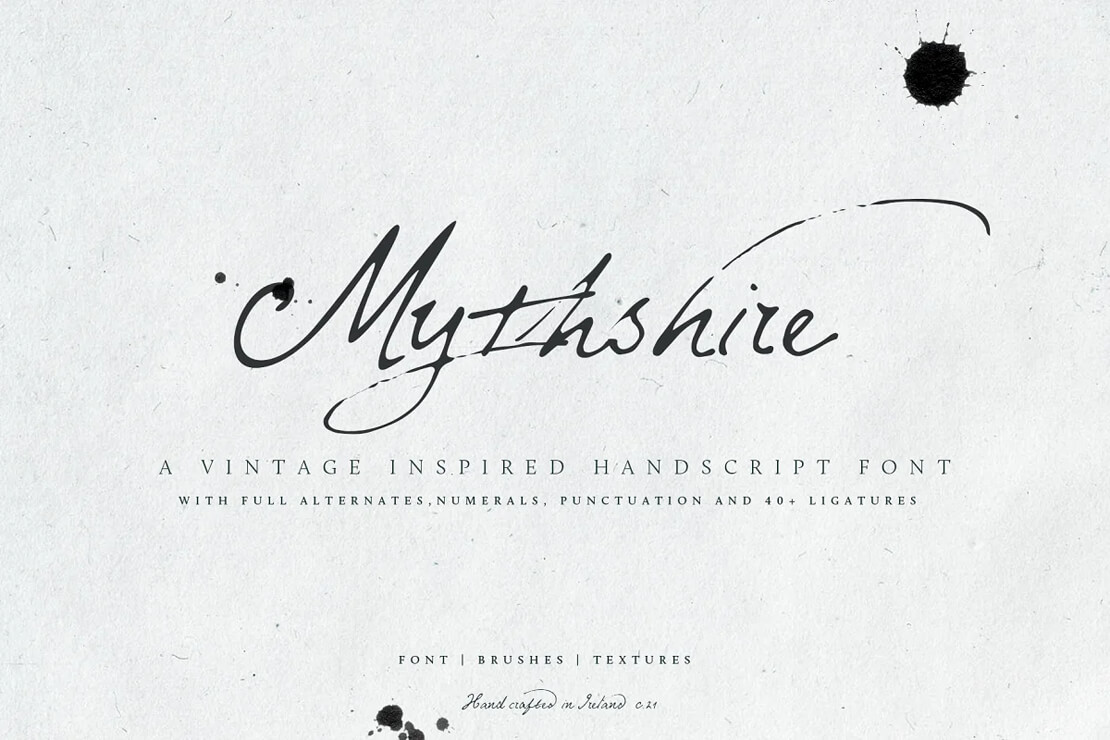
Mittelalterliche Schrift kreativ interpretiert: Medieval Fonts
Mittelalterliche Schrift hat eine faszinierende Anziehungskraft, die durch detailreiche und stilvolle Fonts Ausdruck findet. Die Epoche inspiriert zahlreiche Kreative, die moderne Displayfonts im prunkvollen und mystischen Look gestalten. Diese Übersicht zeigt ausgewählte mittelalterliche Schriftarten im zeitgemäßen Stil.
Mittelalterliche Schrift
Faszination Mittelalterliche Schrift
Mittelalterliche RitterrüstungSchriftarten, die das Mittelalter reflektieren, haben in Bereichen wie Fantasy-Literatur, Rollenspielen, Historiendramen und Videospielen eine große Bedeutung. Mittelalterliche Schrift verleiht diesen Projekten Authentizität und Tiefe. Dabei sind viele dieser Fonts Neuschöpfungen, inspiriert durch gotische und frakturartige Formen, die das ästhetische Bild des Mittelalters prägen.
Zu den historischen Einflüssen zählt die Fraktur-Schrift, die in der Gotik verwurzelt ist und heute oft mit dem Mittelalter in Verbindung gebracht wird. Die hier vorgestellten Fonts nehmen diese Stilrichtungen auf und verbinden sie mit modernen typografischen Features wie alternativen Zeichen und Swashes, die mehr gestalterische Freiheit ermöglichen.
Mittelalterliche Schriftarten zum Downloaden
Diese Auswahl zeigt Beispiele für mittelalterliche Schriftarten, die kostenfrei oder kostenpflichtig erhältlich sind und eine historische, aber dennoch moderne Atmosphäre erzeugen. Typische Einsatzgebiete sind Branding, Covergestaltung für Romane, Eventposter oder Kleidung. Mit variierenden Opentype-Features wie Ligaturen und Swashes werden die Fonts für kreative Projekte nutzbar.
Mittelalterliche Schrift von Creative Media Lab
Mittelalter-Schrift Baselard von KadekUnter dem Label „Creative Media Lab“ bietet Designer Kadek Schriftarten im mittelalterlichen Stil an, darunter Baselard*, Lordish* und Cattedrale*. Diese Fonts sind stark kalligrafisch geprägt und eignen sich für den Einsatz auf Labels, in der Mode oder im Bereich Gothic.
Belmont – Ein Fantasy-Font mit mittelalterlichem Flair
Belmont Fantasy- und Mittelalter-FontDer Font „Belmont“ bringt mittelalterliche Schriften mit einem Fantasy-Twist und bietet Schnitte für verschiedene Anwendungen. Internationaler Sprachsupport und alternative Zeichen machen Belmont für zahlreiche Projekte interessant.
Wolvercote – Inspiration durch Fantasy-Romane
Wolvercote - von Fantasy-Romanen inspirierte SchriftartMit „Wolvercote“ hat Christian Laliberte eine von Fantasy-Romanen beeinflusste mittelalterliche Schrift geschaffen. Die geschwungenen Formen und der Vintage-Stil machen diesen Font besonders für Projekte im Literatur- oder Film-Bereich interessant.
Mythshire: Mittelalterliche Handschrift
Mythshire: Vintage inspired Handscript FontDie Handschrift „Mythshire“ erinnert an historische Kalligrafie und verleiht Texten einen authentischen, eleganten Touch. Enthalten sind zahlreiche Ligaturen und alternative Zeichen, die die mittelalterliche Schrift abrunden.
Candelabra und andere Gothic-Fonts
Der Medieval Font CandelabraDer Font „Candelabra“ von Twinbrush Image Forge ist ideal für Fantasy-Genre-Anwendungen und wirkt mystisch und dunkel. Perfekt für Buchcover, Kleidung und mehr.
Aviorte: Ritterliche Mittelalterliche Schrift
Aviorte Mittelalter Font„Aviorte“ bringt einen Hauch von Ritterromantik und ist für zahlreiche Einsatzgebiete geeignet – von Branding-Projekten bis hin zu T-Shirts und Abzeichen.
DreiFraktur – eine kostenlose mittelalterliche Schrift
Kostenlose Mittelalter-Schrift DreiFraktur„DreiFraktur“ von Jay Cobs orientiert sich an gotischen Stilen und ist kostenlos verfügbar, ideal für private Projekte oder Retro-Designs.
Solaire und Exocet – Historisch inspirierte Schriften
Solaire: H. P. Lovecroft Font„Solaire“ und „Exocet“ verkörpern den mystischen Charakter des Mittelalters und passen gut zu düsteren und phantastischen Szenarien. Während „Exocet“ von Blizzard für „Diablo“ verwendet wurde, ist „Solaire“ durch literarische Inspirationen geprägt.
Asgaard und Magensburg
Vikinger-Schriftart für Mythologie„Asgaard“ bietet sich für nordische Mythologie-Projekte an und lässt sich durch seine Layer gut individualisieren. „Magensburg“ ist eine kostenlose Schrift, die besonders in Logos oder für private Projekte eine mittelalterliche Atmosphäre erzeugt.
Endor und Braveheart – Gothic und Blackletter im Mittelalter-Stil
Endor Vampir-Font„Endor“ und „Braveheart“ sind Gothic-Fonts, die in Blackletter-Optik ein dramatisches Schriftbild erzeugen. Ideal für Filmtitel, Buchcover oder Merchandise.
Odd Times Typeface und Livingstone
Odd Times Mittelalter-SchriftMit „Odd Times“ wird die mittelalterliche Schriftkultur durch geschwungene Blackletter-Formen und EPS-Grafiken ergänzt. „Livingstone“ hingegen bringt eine klassische Blackletter-Ästhetik in Bars, Tattoo-Shops oder Bieretiketten zur Geltung.
Fazit
Mittelalterliche Schrift lebt durch die Vielfalt an Stilen, die sie bietet – von der eleganten, kalligrafisch inspirierten Handschrift bis hin zu schweren Blackletter-Formen. Diese Schriften lassen sich in unzähligen Projekten einsetzen und bringen eine historische Atmosphäre, die zugleich modern interpretiert werden kann. Ob für Fantasy-Geschichten, Eventplakate oder das Branding von Produkten: mittelalterliche Schriftarten schaffen eine visuelle Tiefe und sorgen für einen einzigartigen Wiedererkennungswert.
Die Faszination für mittelalterliche Schriftarten wird in der Gestaltung und Ästhetik deutlich, die an Ritter, Burgen und mystische Geschichten erinnert. Für Projekte, die auf eine besondere Atmosphäre setzen, bieten diese Fonts eine entsprechende Grundlage.